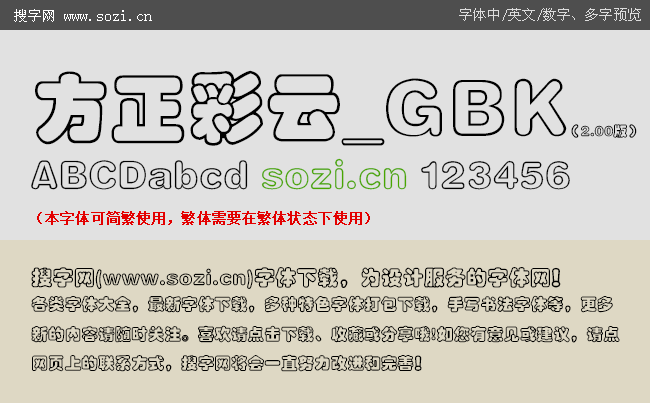
方正彩云_GBK
搜字網(wǎng)提供方正彩云_GBK中文藝術(shù)字體下載,方正彩云_GBK是一款應(yīng)用于設(shè)計方面的中文簡體漢字,該字體呈空心狀,線條細膩,整體效果十分出色,GBK碼收字更全,可以應(yīng)用于廣告設(shè)計、名片設(shè)計、包裝印刷、產(chǎn)品設(shè)計等應(yīng)用。
• 風(fēng)格類別: 琥珀體